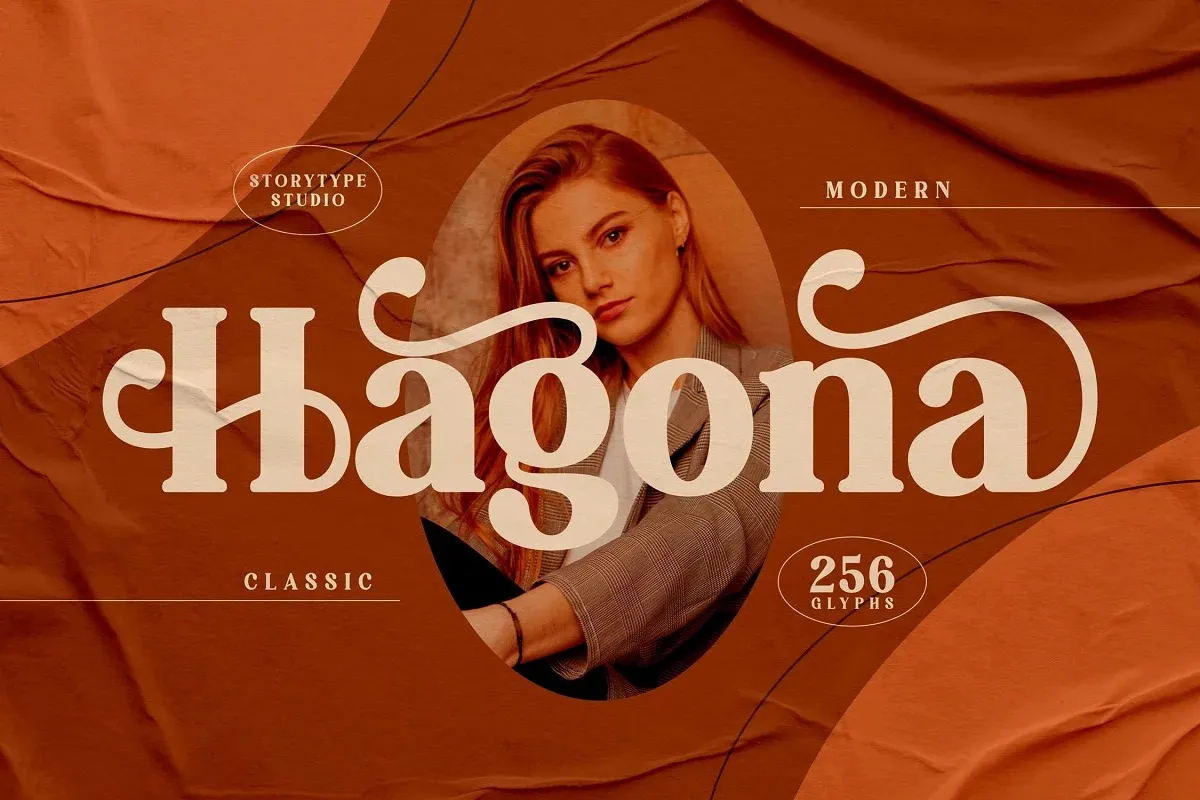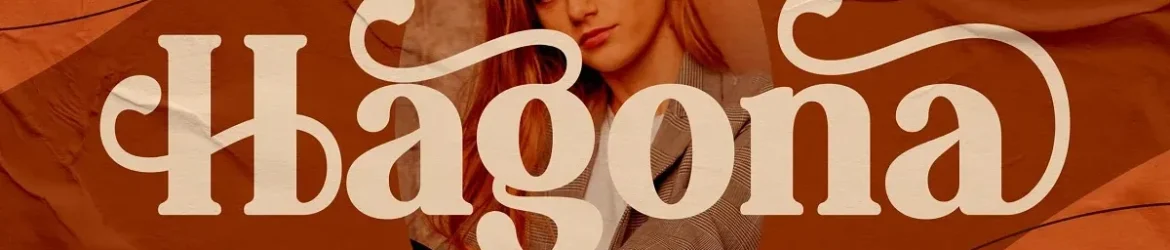
A Hagona Font é uma nova serif moderna apresentada pelo Storytype Studio. Esta tipografia oferece nuances elegantes e sofisticadas para designers que buscam expressar elegância e luxo, seja no design de logotipos para marcas de alta qualidade, títulos de livros ou filmes, em marcas de moda, revistas, cartões personalizados, citações e muito mais. Suas linhas curvadas e detalhes refinados criam um contraste perfeito entre os elementos textuais e gráficos, tornando-a uma opção ideal para qualquer aplicação que necessite de uma aparência sofisticada e profissional. A Hagona Font é sua ferramenta perfeita para trazer vida à sua criação visual.